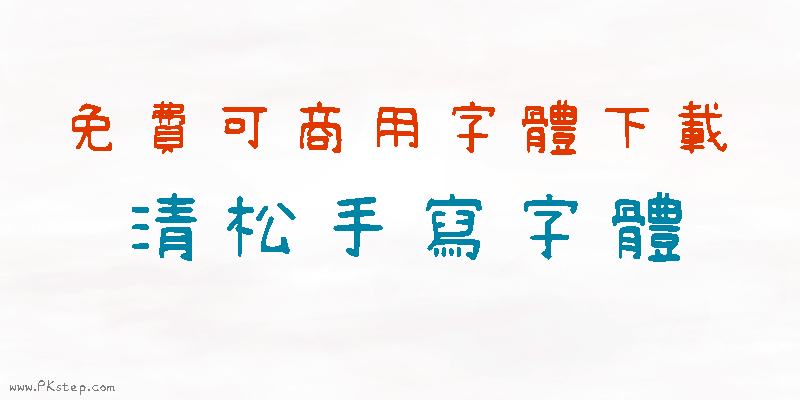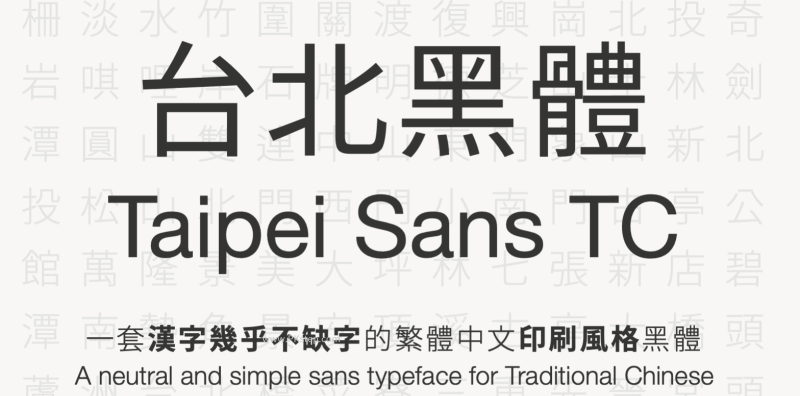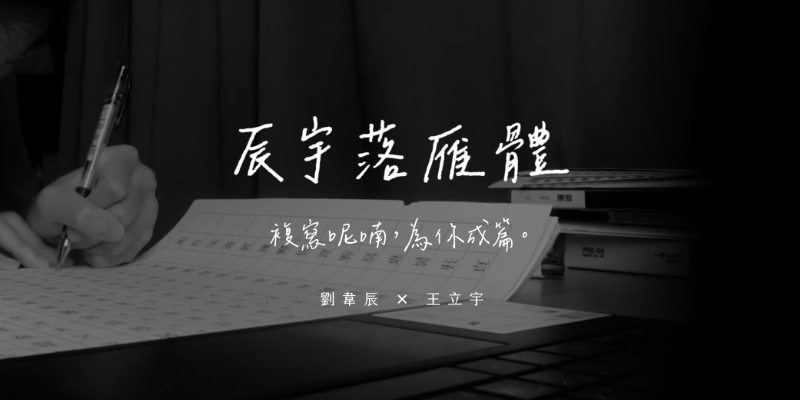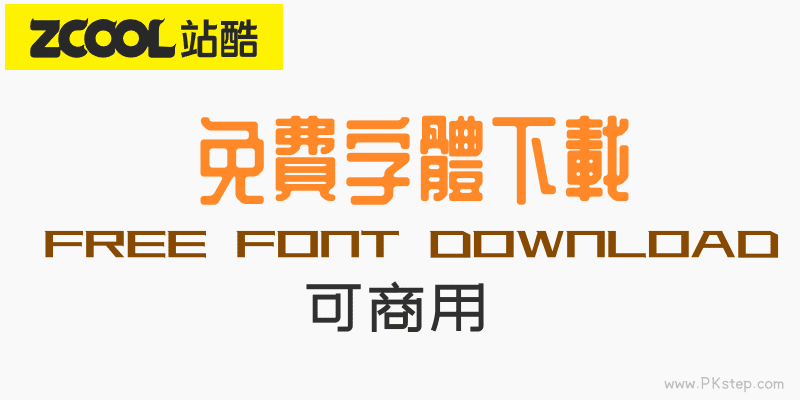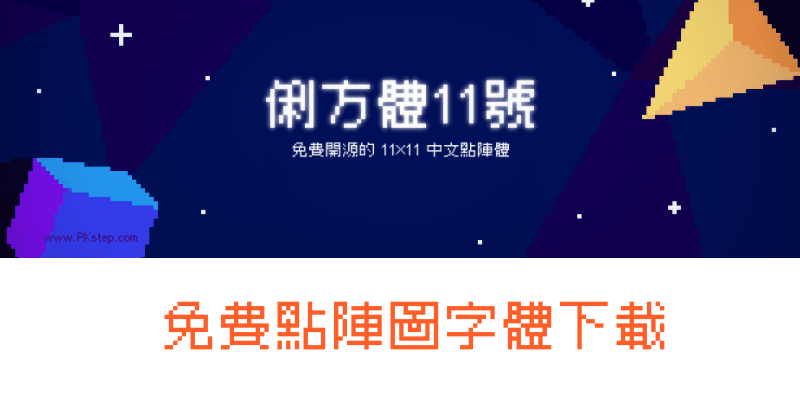
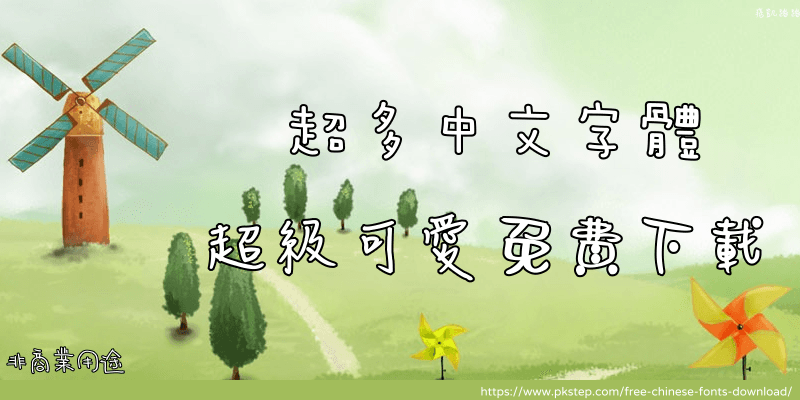
2025 最多字體下載網站!繁體中文字體免費下載,安裝字型必看!超多中文字體,可商用手寫字型、童童體、娃娃體、藝術字體、個性化特殊文字、可愛字體,無論是POP美工製作還是海報、簡報設計都能派的上用場,可用於印製賀卡、個人名片或任何學術上的用途,繁體中文和簡體都有哦,部分字型若用於商業用途需支付使用費。若想快速查看套用樣貌可使用WinFontsView字型預覽工具,行動裝置請看→手機字體下載App;英語字體請看這篇→免費英文字體下載。
新蒂字體
進入新蒂字體,免費中文字體下載,想到喜歡的字體,大大的給它按下載~免費用於個人網站、圖片、非商業用途,字體還支援簡體和繁體中文,快進來挖寶吧,不定期更新最新的字型。
清松手寫體
清松手寫體是來自順其字然所開發的字體,可供個人與商業100%免費使用!共包含3款不同款式的可愛風字體免費下載安裝,完整的中文、英文、標點符號和數字字庫,不怕有漏字問題。
思源Noto字體家族
思源Noto字體家族支援簡體中文、繁體中文、日文和韓文,有思源黑體(無襯字)、思源宋體(襯字)、思源柔黑體(圓角)三種,可供商用與免費下載。
悠哉字體
悠哉字體基于 Y.OzFont 的手寫風格的字體,繁體中文也有支援。
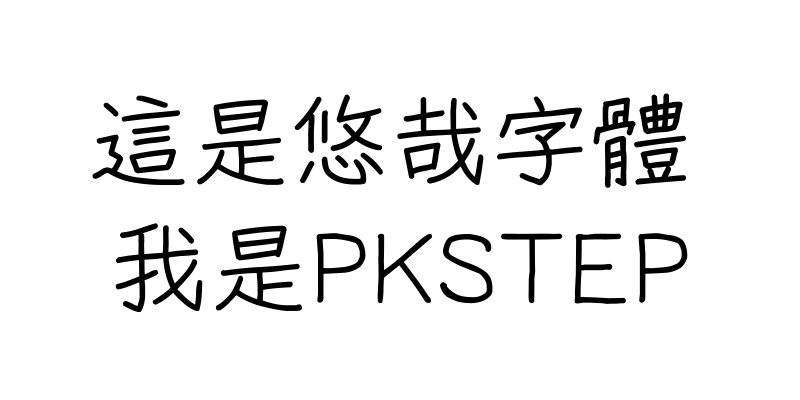
少女體、個性風、手寫字體、藝術字體
免費的字體下載!少女體、個性風、手寫字體、藝術字體,可供個人與商業使用,字體來源為日本的網站。
台北黑體Taipei Sans TC
可商用字體,由翰字鑄造以思源黑體為基礎,投入的開源字型改作-台北黑體Taipei Sans TC,支援英文、特殊符號、繁體中文、簡體中文、日本漢字…非常完整的漢字庫,幾乎不缺字。
王漢宗自由字型
王漢宗自由字型,由台灣中原大學數學系王漢宗教授研發、GPL授權,可免費使用下載於個人或商業。包含空心體、海報體、波浪體、注音等各式可愛的手寫字體,王漢宗免費字型下載包1、王漢宗免費字型下載包2。總共多達42種中文字型!
辰宇落雁體
辰宇落雁體,免費可商用繁中手寫字體下載。
免費中文字體下載網站
免費中文字體下載網站,這邊也蒐集了多款免費的繁體中文字體下全,可下載ttf安裝檔,可商用字型。
瀨戶字體
瀨戶字體SetoFont&小瀨字體支援中文繁體、簡體、英文、日文字形。
FontBear日漢英字體
FontBear日漢英字體下載,可供商用的手寫日系風字體,雖然來自日本網站,但繁體中文也能套用喔!
免費書法字體
免費書法字體下載,草書、行書、隸書,滿滿中國風的毛筆字體!可商用。
滑油字體
WD-XL 滑油字體免費下載。
Google Fonts繁體中文字體
Google Fonts繁體中文字體,分別為cwTeXKai楷體、cwTeXHei黑體、cwTeXYen圓體、cwTeXFangSong仿宋體、cwTeXMing明體
免費可商用中文字體下載
整理了來自日本網站提供的免費可商用字體懶人包:免費可商用中文字體下載,有可愛手寫體、圓體、藝術體…等多達10幾種好看的字型。
獅尾字體家族
獅尾字體家族,免費可商用字體下載。
獅尾右下腿黑體、獅尾右下圓黑體、獅尾飛腿黑體、獅尾飛鏢黑體、獅尾火腿黑體、獅尾火柴黑體、獅尾骨腿黑體、獅尾骨頭黑體、獅尾斧腿黑體、獅尾斧頭黑體、獅尾喇腿黑體、獅尾喇叭黑體、獅尾惡腿黑體、獅尾惡魔黑體、獅尾麥腿黑體、獅尾麥克黑體、獅尾詠腿黑體獅尾詠春黑體、獅尾鋸腿黑體、獅尾鋸齒黑體、獅尾尖刺黑體、獅尾福腿黑體、獅尾福音黑體、獅尾D滷腿黑體、獅尾德魯納黑體、獅尾彎腿黑體、獅尾彎黑體、獅尾霓腿黑體、獅尾霓黑體、獅尾蝙蝠圓體、獅尾牙膏圓體、獅尾三角黑體、獅尾螺帽腿黑體、獅尾螺帽黑體、獅尾B2腿黑體、獅尾B2黑體、獅尾腿圓、獅尾彩虹腿、獅尾XD珍珠、獅尾D露西、獅尾半月字體、台灣圓體、獅尾圓體、獅尾黑體、獅尾加糖宋體、獅尾B2宋朝、獅尾肉丸、獅尾四季春字體
站酷字體
站酷字體-8款中文字體免費下載,可供商用,有藝術中國風的字體、娃娃體、少女體、布丁體風格的字型。
俐方體11號
俐方體11號-點陣圖字體免費下載,像素風格的字型,收錄快五千個繁體中文字,在中文、標點符號、英文、數字皆可套用。
黑板粉筆字體
爆質感的【黑板粉筆字體】免費下載,可愛的蠟筆風格的手寫字體,支援簡體中文、繁體中文、英文、日文、數字、標點符號。
古文字體
免費的古文字體,包含篆體、明朝體、甲骨文體,皆為可商用,用在製作印章字體、海報、簡報上。
麻將字體
免費麻將字體下載,在電腦顯示中、發、白、五條、一萬、三筒、三條、八萬等文字。
免費POP、原子筆、海報字體下載
來自日本網站所提供的免費POP、原子筆、海報字體下載,可供商用,部分中文字有漏字。
漢鼎系列字體
漢鼎系列字體支援中文繁體、簡體字型。
字體產生器
你也可以使用字體生產器,產生更多藝術字型!
字庫素材下載網
來自中國的字庫素材下載網,幾乎為簡體字範例,但繁體也能用。
自己設計字體
DIY製作屬於自己的字體,守寫字-把自己寫的手寫字變成電腦字體、推薦5款免費的字體設計軟體